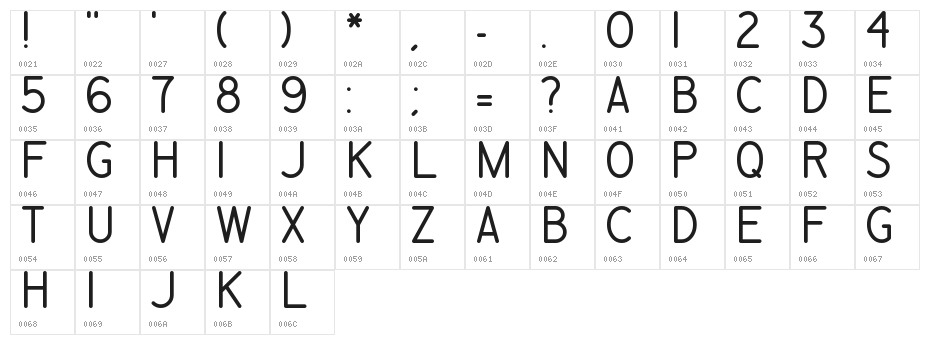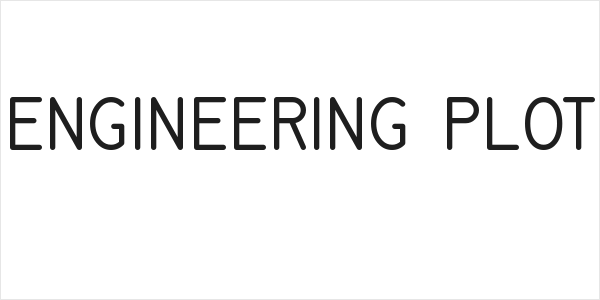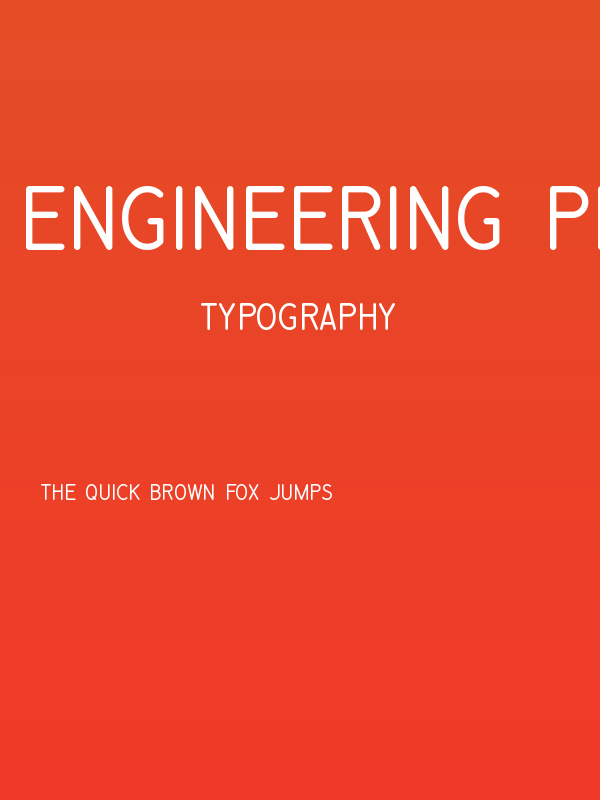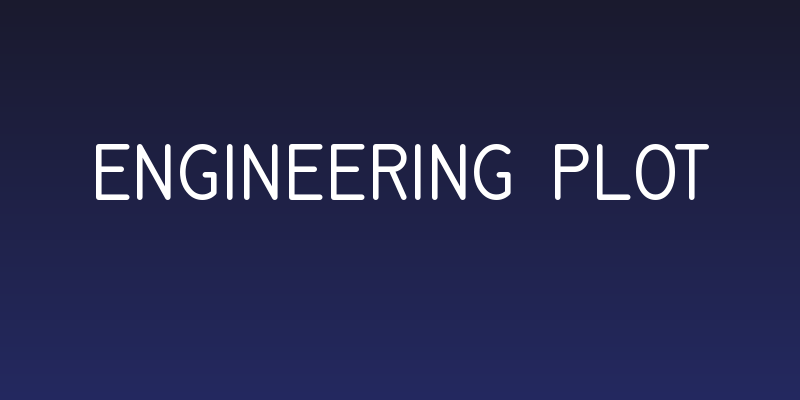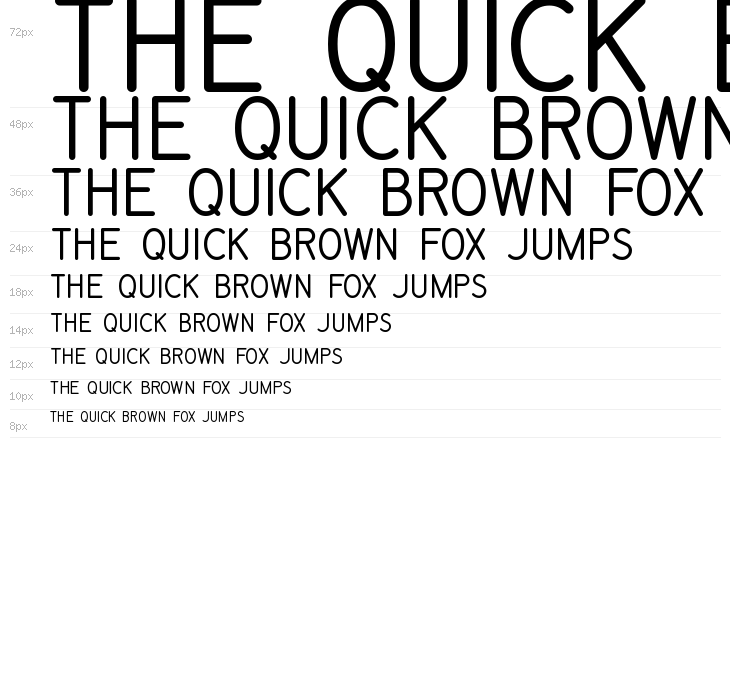
Engineering Plot Font
✎ Sans Serif
| حالة الاستخدام | Technical documents, digital interfaces, branding |
| مشاريع مقترحة | Ideal for technical documents, engineering diagrams, modern branding, and digital interfaces. |